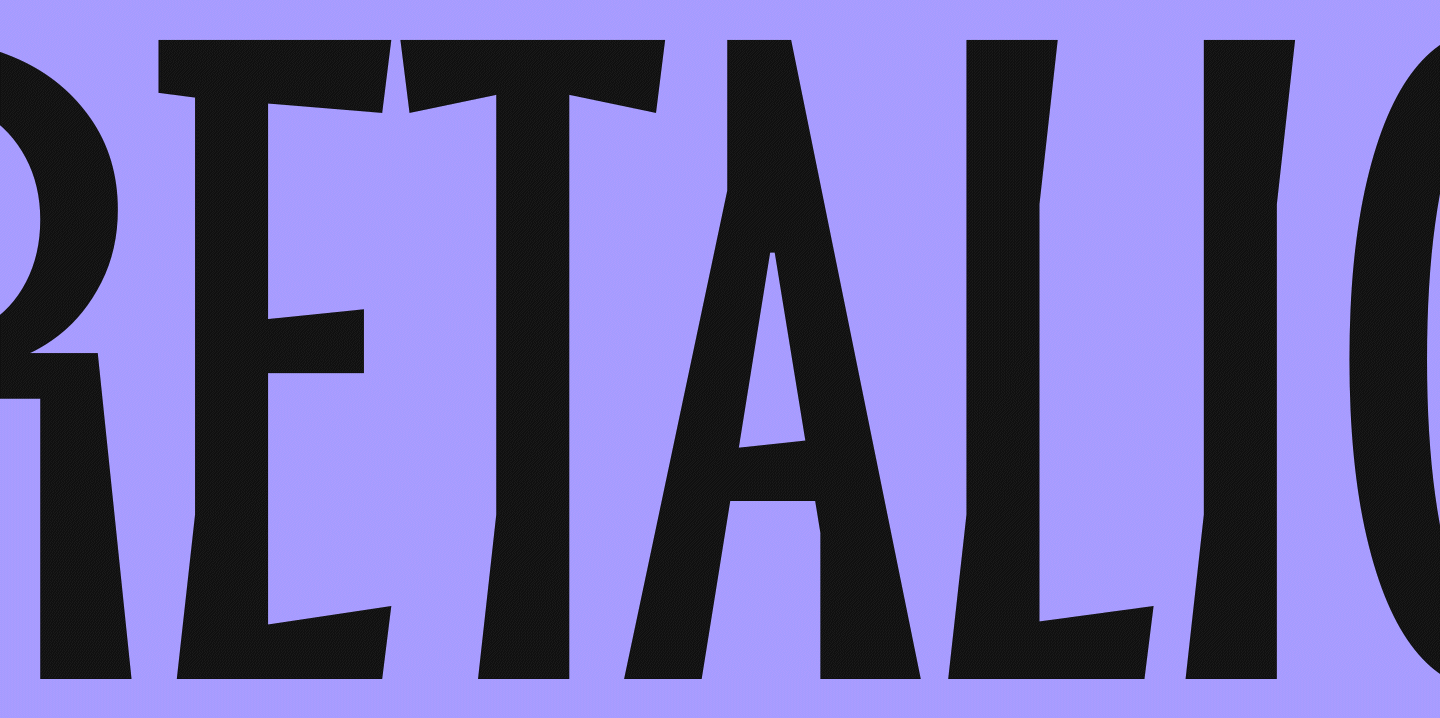
Что такое реталик?
Для начала освежим знания и вспомним, что такое италик, обратившись к нашему шрифтовому словарю.
Италики (тру италики или настоящие италики) — исторически так обозначали только курсивные шрифты. Т.е. наклонные шрифты, где графемы строчных знаков менялись на курсивную форму (true italic). В основном характерны для шрифтов с засечками. Сегодня термин используется в более широком смысле и объединяет тру италики и наклонные шрифты (slant, oblique).
Реталик же — это зеркальный брат италика, то есть обратный курсивный шрифт, наклон которого направлен влево. В буквальном смысле это обратный италик (реиталик).
Без италиков не было бы реталиков. Первые предназначены для выделения частей текста, вторые за счёт непривычного глазу левого наклона ещё больше выделяются и привлекают внимание, добавляя тексту динамики. Реталики очень выразительны, но встречаются редко, так как выглядят довольно необычно.
Для чего нужны реталики и где они используются?
Благодаря своей выразительности реталики чаще всего используются для создания акцентов и привлечения внимания. Особенно гармонично они выглядят там, где нужно передать динамику, ощущение движения. Это может быть спортивный бренд или служба доставки, цирковая афиша или обложка музыкального альбома, обложка книги / журнала или меню ресторана быстрого питания.
Кроме того, есть и неожиданные сферы применения реталиков — их мы покажем чуть ниже.
Разные названия одного понятия
Обратный курсив, контр италик, косой шрифт — вы можете встретить разные термины для обозначения реталика. Напомним, что русскоязычная шрифтовая терминология в целом пока не очень устойчива, поэтому могут встречаться разные трактовки.
Мы в TypeType используем термин реталик, потому что наклонные начертания в нашей словолитне принято называть италиками, а италики с курсивными формами — true italics. Чтобы оставаться в этой системе, мы решили назвать обратный наклон Retalic (полное название — reversed italic).
Вот список терминов, которые могут использоваться для обозначения реталика:
- Contra italics;
- Backslanted;
- Left italic;
- Reverse oblique
- Reversed italic;
- Reclining;
- Reclined italics;
- Left italics;
- Linkskursiv;
- Left-leaning italics.
Не путайте реталик с роталиком!
Ещё один интересный и редкий шрифтовой феномен — роталик. В отличие от италика и реталика, знаки в таком шрифте не наклоняются в правый или левый угол, а как бы «прокручиваются» по часовой или против часовой стрелки, разворачиваются по оси.
Каллиграфические примеры реталиков
Первые курсивные шрифты основаны, конечно же, на письме. И так как большинство людей — правши, наклон вправо был наиболее распространен. Но встречались, хоть и крайне редко, и экземпляры с обратным наклоном.
Неожиданные сферы применения реталиков
Хоть шрифты с обратным наклоном встречаются не так часто, сферы их применения достаточно разнообразны и порой неожиданны.
Реталики в картах
Чаще всего реталики в картографии использовались в Германии, в основном — для обозначения названий рек.
Реталики в надписях на надгробиях
Обратный курсив можно также встретить на надгробиях 19 века.
Реталики для обозначения сарказма
Углубившись в изучение реталиков, вы можете встретить идею о том, что их стоит использовать для обозначения сарказма в тексте. Однако такая идея кажется нам (и многим другим участникам подобных обсуждений) провальной. Сарказм должен считываться в тексте без всяких подсказок. Ведь шутка, которую нужно объяснять — это несмешная шутка.
Индустриальная революция, акцидентные шрифты для рекламы, деревянные шрифты
Вторая индустриальная революция (вторая половина XIX — начало XX века) значительно повлияла на облик шрифтов. В частности, в этот период появилось много акцидентных шрифтов, которые использовались для привлечения внимания, в основном в рекламе и на афишах. За счет непривычного наклона реталики отлично справлялись с этой задачей. Взгляд на них невольно задерживается дольше из-за непривычного направления наклона.
Seven Lines Pica No 2 (1815 г.) с большой вероятностью можно считать первым типографским шрифтом с обратным наклоном.
Интересные представители реталиков — деревянные шрифты словолитни Hamilton Wood Type.
Реталик используется в дизайне обложки «Манифеста сюрреализма» Андре Бретона 1972 года.
А вот акцидентный пример использования реталика времен СССР.
Как мы рисовали реталик?
Недавно в нашей коллекции появился первый реталик — в составе акцидентного шрифта TT Biersal, вдохновленной типографикой первой половины 20 века. Отправной точкой для его создания послужил леттеринг на немецком плакате начала 30-х годов.
Мы рисовали реталик по логике италика, следуя нашей авторской методичке. Знаки «наклоняли», как обычно, разделив по группам: прямые, треугольные, круглые. Подробнее о процессе читайте здесь.
«Реталик я делала уже после италика — мне так было проще, но в целом его можно рисовать независимо от италика. Из-за экстремального наклона очень сильно искажалась толщина стемов, поэтому мы компенсировали ее на глаз. Угол наклона в остальных наших шрифтах не больше 11-12 градусов, и толщина в этом случае если и искажается, то незначительно, буквально на пару пунктов. В этом же шрифте угол наклона составил 40 градусов, поэтому искажение было ощутимым».
Заключение
Как видите, у реталиков довольно интересная история. Однако несмотря на то, что такие шрифты используются давно, они по-прежнему непривычны для нашего взгляда. Но в этом и заключается главное преимущество обратных италиков — они выглядят свежо, небанально и способны удивить. Надеемся, вы найдете вдохновение для экспериментов в нашей статье!